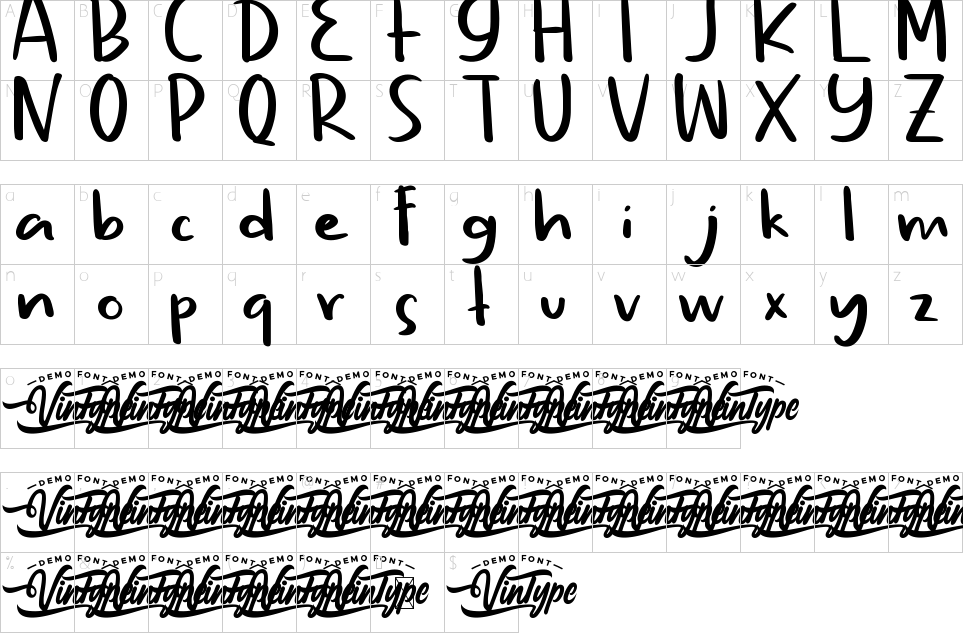
Destiny Universe é uma elegante e envolvente fonte que oferece uma experiência visual única para seus projetos. Inspirada no universo misterioso e encantador do Destino, esta fonte foi cuidadosamente criada por VinType. Com um design minimalista, a Destiny Universe combina elegância com facilidade de uso, o que a torna perfeita tanto para aplicações digitais quanto impressivas físicas. Seu design fluido e sofisticado não só destaca seu conteúdo, mas também adiciona uma sensação misteriosa e intrigante ao projeto. Com sua linguagem suave e elegante, Destiny Universe se adapta a qualquer estilo de design ou aplicação gráfica. Download esta fonte gratuita para Windows e Mac e experimente a diferença que ela pode fazer em seu trabalho. Aproveite esta oportunidade de adicionar um toque único e memorável ao seu próximo projeto.